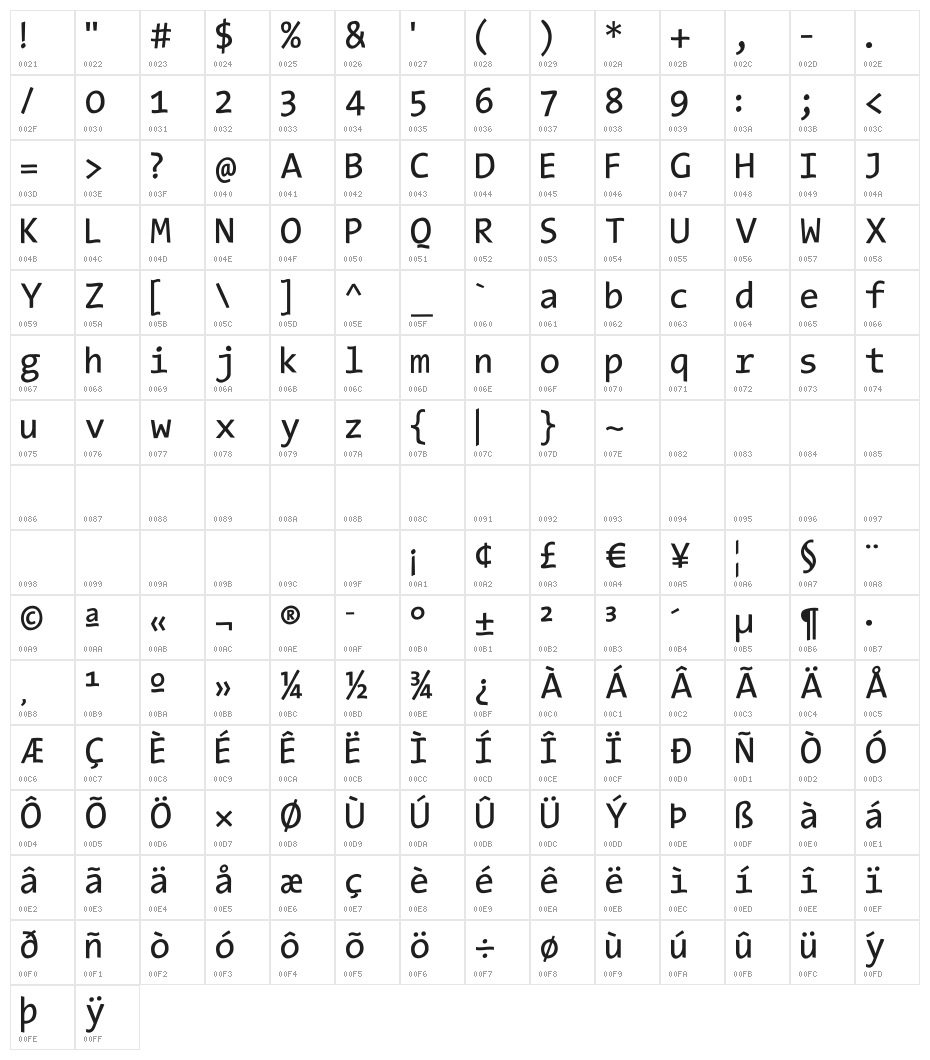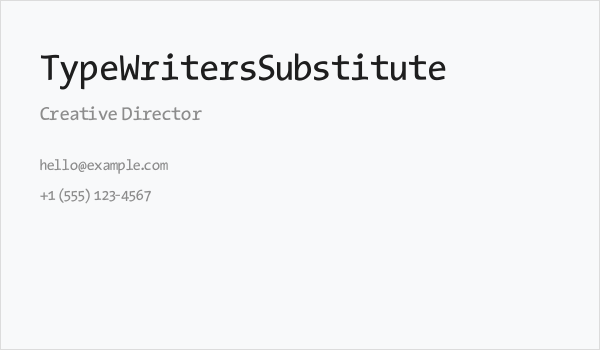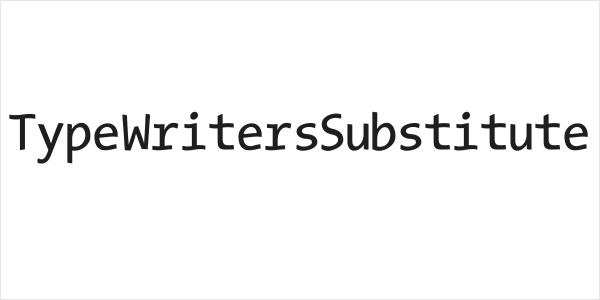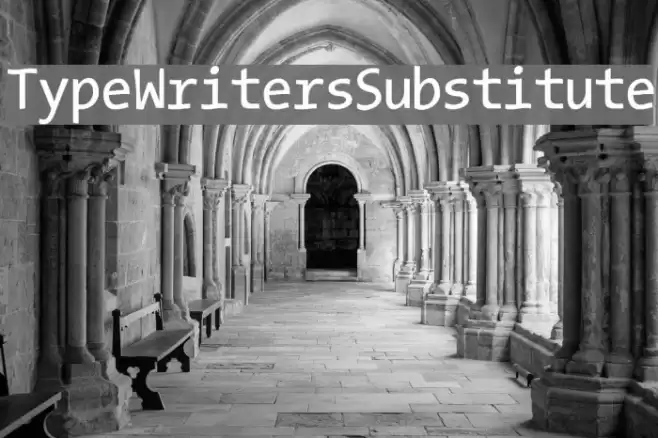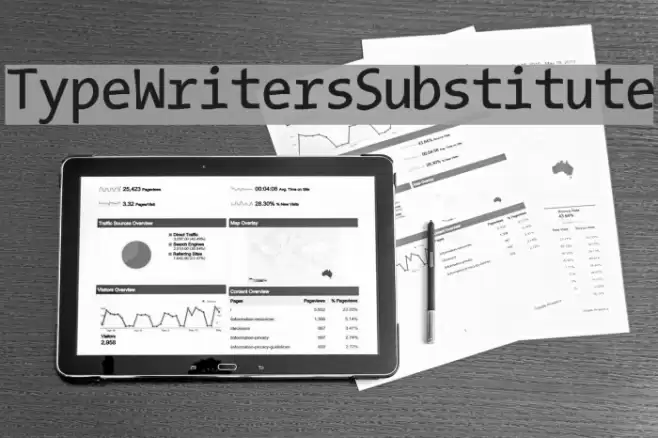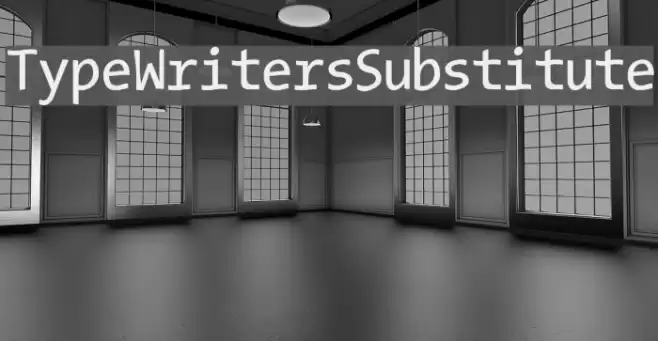
TypeWritersSubstitute Font
| Estilo general | Casual |
| Caso de uso | Headlines, Informal text, Branding |
| Proyectos propuestos | Ideal for children's books, casual branding, greeting cards, and social media graphics. |